为设计师设计的 100 种最佳阿拉伯字体
已发表: 2022-04-28阿拉伯语在现代世界的重要性不容小觑。 作为20 多个国家的官方语言,阿拉伯语在全球拥有约3 亿使用者。
阿拉伯语的真实感觉使阿拉伯语字体成为设计师最抢手的字体类别之一。
从具有真实感觉的创意纹身设计到增强您的数字设计,阿拉伯字体是为您的设计提供独特触感的绝佳工具。 由于其独特的感觉,阿拉伯字体最近变得越来越流行。
以下是您可以使用的前 100 种阿拉伯字体:
顶级阿拉伯字体集合
奥斯托里
Ostouri 的含义在阿拉伯语中是传奇的,就像字体本身一样。 美丽的阿拉伯文字排版和惊人的字母流使它成为各种项目的绝佳选择。
优雅的字母设计使其适用于任何类型的品牌或广告相关内容。
贝斯梅拉 2
字形计数为 119,字体具有直立姿势,属于“符号”家族。 此外,它具有中等重量和宽度。 你可以在这里下载字体。
似曾相识
该字体是半轻量级的,属于“拉丁”(文本和显示)家族类型。 对比度非常低,不是等宽的,可以在这里下载。
代码 2000
属于“Freeform serifs”家族类,字体具有中等粗细和宽度。 该字体的字形数量高达 29574,具有直立的姿势。 你可以在这里下载字体。
帕夏拉
受 8 位图形的启发,如果您正在寻找数字像素化字体, Paxalah是阿拉伯字体的绝佳选择。
对于与任何数字产品广告或相关项目相关的创意设计,这可能是一个很好的字体选择。
安达卢斯
这种半轻量字体具有中等宽度(正常)。 该字体不是等宽字体,也不属于任何指定的家族类。 可以在这里下载。
自由式书法
Free Style Calligraphy 是一款时尚的书法阿拉伯字体,可免费下载。
您可以在任何类型的创意设计中使用此字体,使其看起来更好。 在此处获取有关字体的更多信息
免费衬线
字形计数为 5532,字体不是等宽的。 它具有半轻量级和中等(正常)宽度。 你可以在这里下载。
GE SS 两个加粗
该字体具有“三角形”衬线样式和粗体。 该字体的字形计数为 287,具有普通/联系字母形式。 字体可以在这里下载。
DejaVu Sans Bold
属于“拉丁(文本和显示)”,字体有粗体。 这个中等(正常)宽度可以在这里下载。
阿尔及利亚
字形计数为 95,此字体不是等宽字体。 来自“装饰”家族类型,字体具有半粗体字重。 你可以在这里下载。
UKIJ Moy Qelem
该字体具有“Cove”衬线样式。 它属于“Freeform serifs”家族类,可以在这里下载。
哈马字体
Hamah 是另一种高质量的阿拉伯字体,您可以在任何类型的创意设计、广告牌、网站、徽标和任何其他类似项目中使用它。
字体大胆而时尚,以确保您拥有适合您项目的完美设计。 在此处获取更多信息
DejaVu Sans Extra Light
字形计数为 1540,该字体属于“拉丁(文本和显示)”系列类型。 这种额外的轻量字体具有中等(正常)宽度,可以在此处下载。
GE SS 两灯
字体具有中等(正常)粗细和宽度。 它属于“拉丁语(文本和显示)”家族类型,可以在这里下载。
GE SS 两中
GE SS Two Medium 字体不属于任何指定的家族类别,字形计数为 287。此字体具有“三角形”衬线样式,可在此处下载。
DejaVu Sans Condensed Bold
字形计数为 4988,该字体具有粗体和压缩比例。 你可以在这里下载。
贝斯梅拉 3
此字体的字形计数为 89,并且不是等宽字体。 它属于“符号”家庭类别,具有中等(正常)的重量和宽度。 你可以在这里下载。
GE 第纳尔一号培养基
该字体具有“三角形”衬线样式,字形计数为 287。可以在此处下载。
DejaVu 无单声道
具有“Normal sans”衬线样式,字体具有等宽比例。 这个半轻量级可以在这里下载。
B 阿拉伯风格
字体具有直立姿势和中等(正常)宽度。 可以在这里下载。
UKIJ 迪瓦尼
该字体的字形计数为 1025,具有“Cove”衬线样式。 这种属于“拉丁文(文本和显示)”的字体可以在这里下载。
GE SS文字灯
字形计数为 287,字体具有中等(正常)宽度,不属于任何指定的系列类别。 可以在这里下载。
Terafont-Chandan
这种半轻量字体具有中等(正常)宽度,可以在此处下载。
贝斯梅拉 1
这种半轻量字体具有中等(正常)宽度。 可以在这里下载。
Ara Sym 斋月 3
字形计数为 96,字体不是等宽的,并且具有直立的姿势。 可以在这里下载。
达斯特尼维斯
属于 'Script' 系列类型,该字体的字形计数为 255,可在此处下载。
B幻想
这种半轻量字体不是等宽的,并且具有直立的姿势。 你可以在这里下载。
DejaVu Sans Mono Bold
属于“拉丁(文本和显示)”系列类型,该字体的字形计数为 3029。该字体具有“普通无衬线”样式,可在此处下载。
GE 第纳尔 2 中号
GE Dinar Two Medium 字体具有独特的“三角形”衬线样式。 可以在这里下载。
MCS 巴斯马拉 正常
该字体的字形计数为 96。它具有中等(正常)宽度和粗细,并且不是等宽的。 你可以在这里下载。
阿加伊斯兰短语
字体具有正常宽度类型和直立姿势。 可以在这里下载。
DejaVu Sans Oblique
这种半轻量字体具有“普通无衬线”风格,可以在此处下载。
GE 第纳尔一灯
字形计数为 287,这种字体是轻量级的。 可以在这里下载。
通用电气流量
这种属于“拉丁(文本和显示)”系列类型的字体的字形计数为 284,可以在此处下载。
UKIJ库菲耶
该字体具有“Cove”衬线样式和半轻量级。 它不是等宽的,可以在这里下载。
B Nazanin 粗体字
该字体具有粗体笔画粗细,并且不是等宽字体。 可在此处免费下载。
阿拉西斋月 2
这种属于“拉丁(文本和显示)”系列类型的字体的字形计数为 96,并且不是等宽的。 可以在这里下载。
阿拉伯语纳斯赫 SSK
阿拉伯语 Naskh SSK 字体不是等宽字体。 这个半轻量级可以在这里下载。
UKIJ 迪瓦尼汤姆
该字体具有“Cove”衬线样式,并且不是等宽字体。 这个中等重量可以在这里下载。
MCS Swer Al_Quran 2
该字体不属于任何定义明确的家族类别,字形计数为 95。可以在此处下载。
撒马尔罕正常
字体不是等宽的,并且具有直立的姿势。 这个半轻量级可以在这里下载。
GE SS TV Bold
该字体不属于任何指定的族类。 具有现代比例和 287 字形计数的字体可以在这里下载。
GE 第纳尔两灯
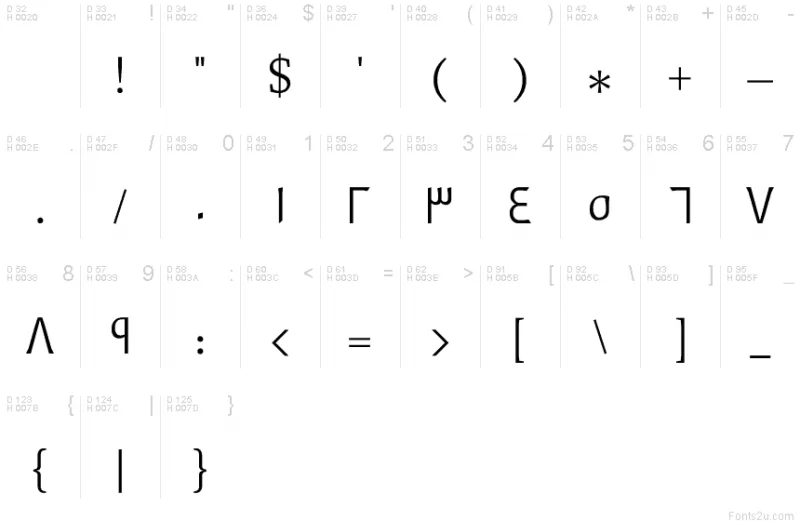
该字体具有轻量级且具有中等(正常)宽度。 它有一个“三角形”衬线样式,可以在这里下载。
GE SS 文本中号
GE SS Text Medium 字体的字形计数为 287,可在此处下载。
UKIJ 库利亚兹马
该字体具有“Cove”衬线样式,属于称为“Freeform serifs”的家族类。 可以在这里下载。
MCS书名6
字形计数为 94,此字体不是等宽字体。 它不属于任何指定的家庭类别,可以在这里下载。
B阿什亚
这种半轻量字体具有中等(正常)宽度和直立姿势。 你可以在这里下载这个字体。
DejaVu Serif 浓缩斜体
此字体具有“方形”衬线样式。 它不属于任何指定的家庭类,可以在这里下载。
B艾勒姆
该字体的字形计数为 286。它具有半轻量和正常宽度类型。 在此处下载字体。
GE Flow 粗体
GE Flow Bold 字体具有粗体和“三角形”衬线样式。 可以在这里下载。
Chrysanthi Unicode 正则
该字体具有半轻量级和中等(正常)宽度。 可在此处免费下载。
GE SS 文本粗体
该字体属于“拉丁(文本和显示)”系列类型,具有“三角形”衬线样式。 你可以在这里下载。
UKIJ 迪瓦尼·卡瓦克
该字体的字形计数为 1009 和半轻量级。 可以在这里下载。
UKIJ图兹汤姆
这种字体具有中高对比度和半轻量级。 可在此处免费下载。
GE SS 独特的光
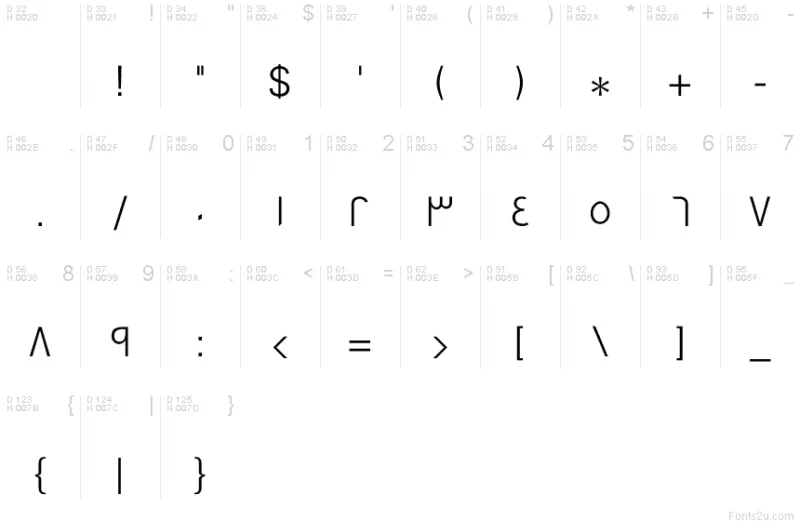
该字体具有“三角形”衬线样式和现代比例。 你可以在这里下载。
阿拉伯语 Kufi SSK
该字体不属于任何指定的家族类,并且具有粗体 mac 样式。 可以在这里下载。
UKIJ Diwani Yantu
属于名为“Freeform serifs”的家族类,该字体具有中等(正常)宽度,可以在此处下载。
GE SS 独特的粗体
该字体属于“拉丁(文本和显示)”家族类型,具有现代比例。 可以在这里下载。
Hacen 沙特阿拉伯
字形计数为 360,字体不是等宽的,并且具有规则的自然图案。 可以在这里下载。
GE东超粗体
该字体具有“三角形”衬线样式并具有粗体字重。 这个字体可以在这里下载。
MCS P_穆罕默德
字形计数为 80,该字体具有中等(正常)粗细和宽度,可以在此处下载。
B达瓦特
该字体不属于任何指定的家族类别,并且具有直立的姿势。 可以在这里下载。
GE SS 三灯
字体具有规则的图案性质和现代的比例。 可以在这里下载。
内马德
此字体不属于任何指定的家族类别,字形计数为 81。可以在此处下载。
MCS Swer Al_Quran 1
这种半轻量字体具有中等(正常)宽度。 图案自然是规则的,可在此处免费下载。
B Esfehan Bold
该字体的字形计数为 286,并遵循斜体 mac 样式。 它有一个直立的姿势,可以在这里下载。
GE 第纳尔一号中等斜体
该字体具有中等(正常)粗细和宽度,可以在此处下载。
MCS 书名 4
MCS Book Title 4 字体的间距不是等宽的,它具有半轻量级。 可以在这里下载。
阿拉伯舞蹈中等斜体
该字体的字形计数为 127,属于“拉丁(文本和显示)”系列类型。 它可以在这里下载。
GE Thameen Demi Bold
该字体不属于任何指定的系列类,并且具有“三角形”衬线样式。 可在此处下载。
GE 第纳尔一浅斜体
这种轻量字体具有中等(正常)宽度。 它有一个“三角形”衬线样式,可以在这里下载。
Kacst 图书
字体具有中等(正常)粗细和宽度。 它遵循规则模式并且不是等宽的。 在此处下载此字体。
MCS Swer Al_Quran 3
MCS 书名 3
该字体不属于任何指定的族类,并且具有常规模式。 可以在这里下载。
B组合
这种外国阿拉伯字体有半轻量型和普通宽度型。 你可以在这里下载。
Kacst 标题 L
字形计数为 401,字体具有中等(正常)粗细和宽度。 可以在这里下载。
爪夷文库菲
这种半轻量字体具有中等(正常)宽度。 可以在这里下载。
B Koodak 大纲
这种半轻量字体有一个直立的姿势,可以在这里下载。
Ukij Tuz Nekish
该字体具有“Cove”衬线样式。 这种中等粗细字体不是等宽字体。 你可以在这里下载。
Lateef 字体
Lateef 字体以著名的信德神秘主义者和诗人 Shah Abdul Lateef Bhitai 命名,是一种漂亮的阿拉伯字体,您可以免费下载并在您的项目中使用。 你可以从这里下载字体。
Baloo Bhaijaan 字体
如果您正在寻找重量级的粗体字体设计,这里是您的不错选择。 Baloo Bhaijaan 字体提供九种印度文字和拉丁文字,非常适合任何项目。